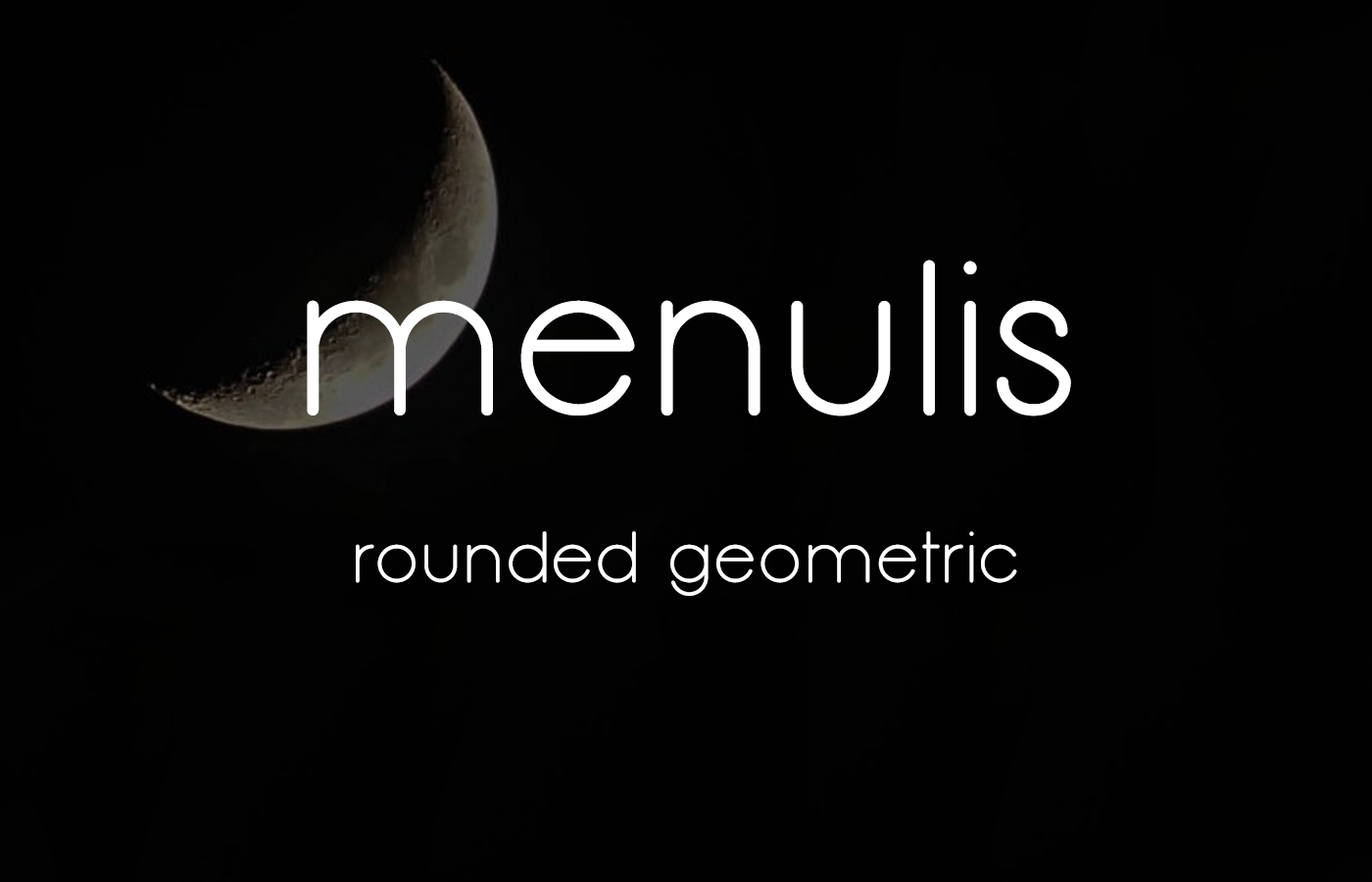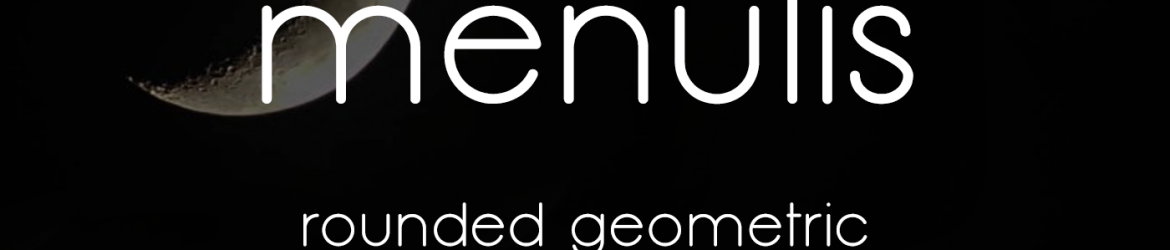
A Menulis é uma fonte sans serif criada pelo designer Hamilton que oferece um estilo fluido e moderno, perfeito para ambientes digitais envolventes. Com linhas finas e formas levemente arredondadas, essa fonte deixa seu design mais atraente e descolado sem perder o foco claro e objetivo. A Menulis se destaca por sua capacidade de proporcionar uma experiência visual envolvente que combina elegância minimalista com um toque moderno. Para quem deseja dar valor à esta fonte, as contribuições são apreciadas para ajudar no desenvolvimento contínuo deste excelente recurso gráfico. Se você acha que está recebendo algo de qualidade, considere fazer uma doação de maneira que seja justa e satisfatória tanto para o designer quanto para você, tornando assim uma experiência colaborativa muito gratificante.